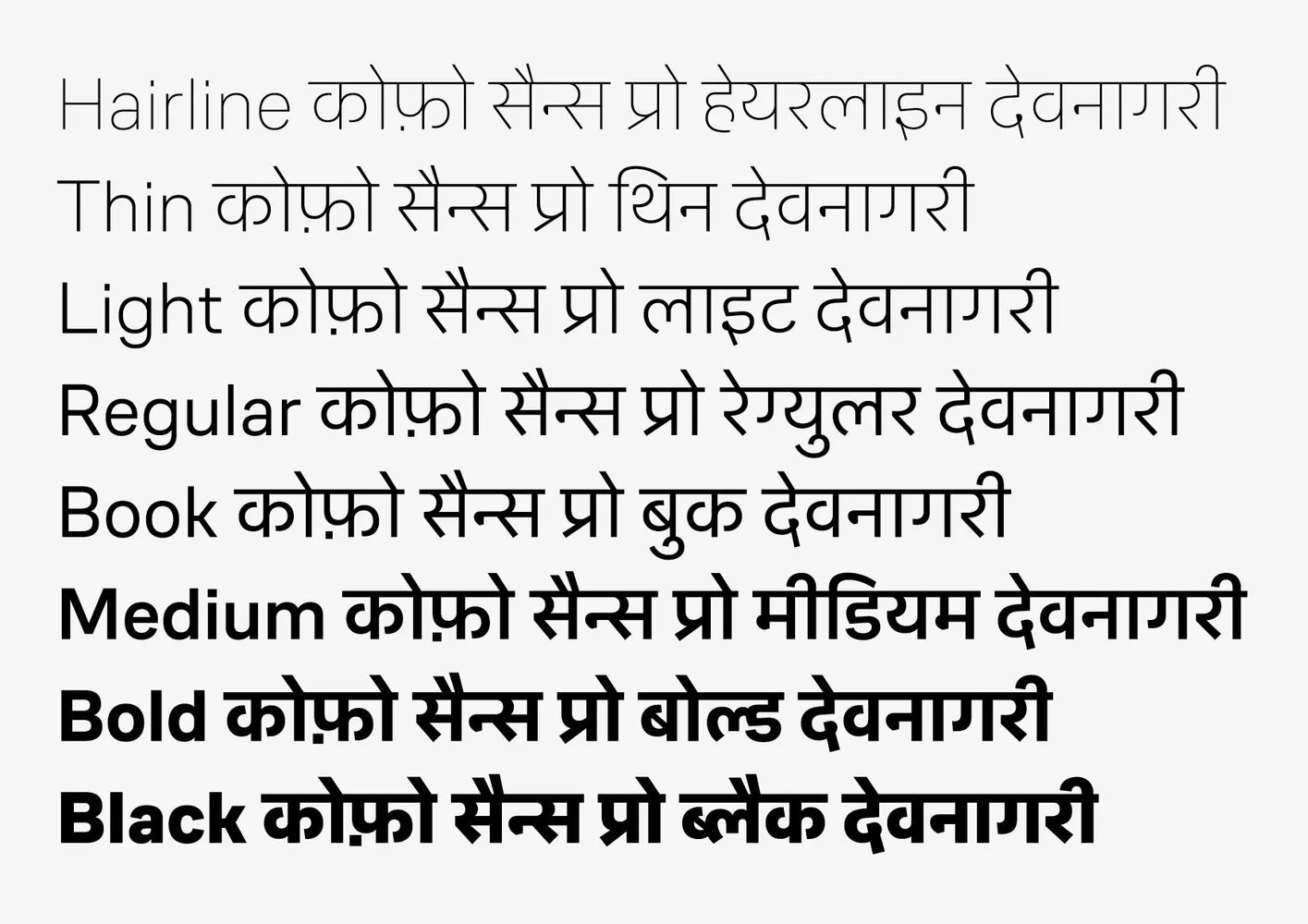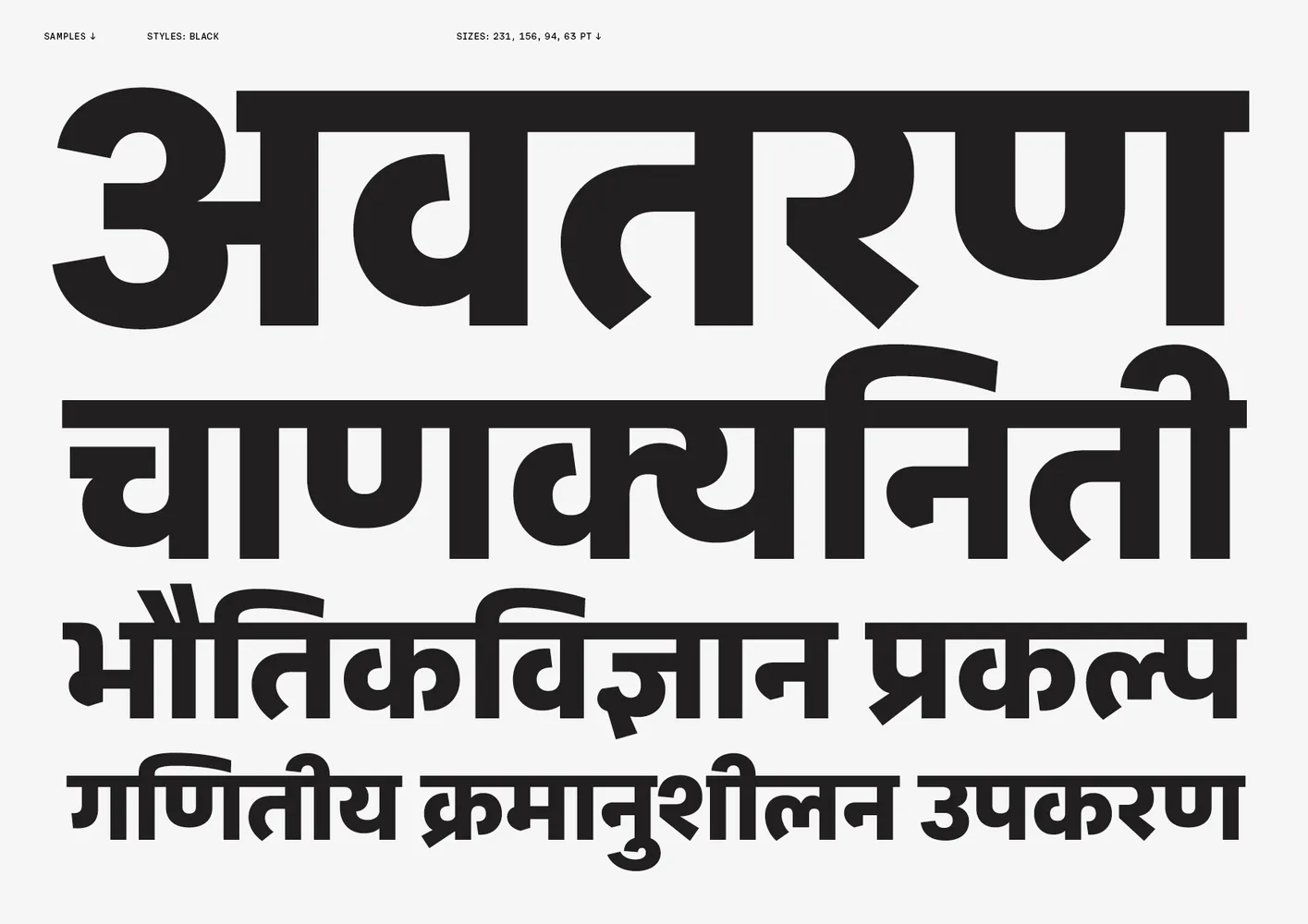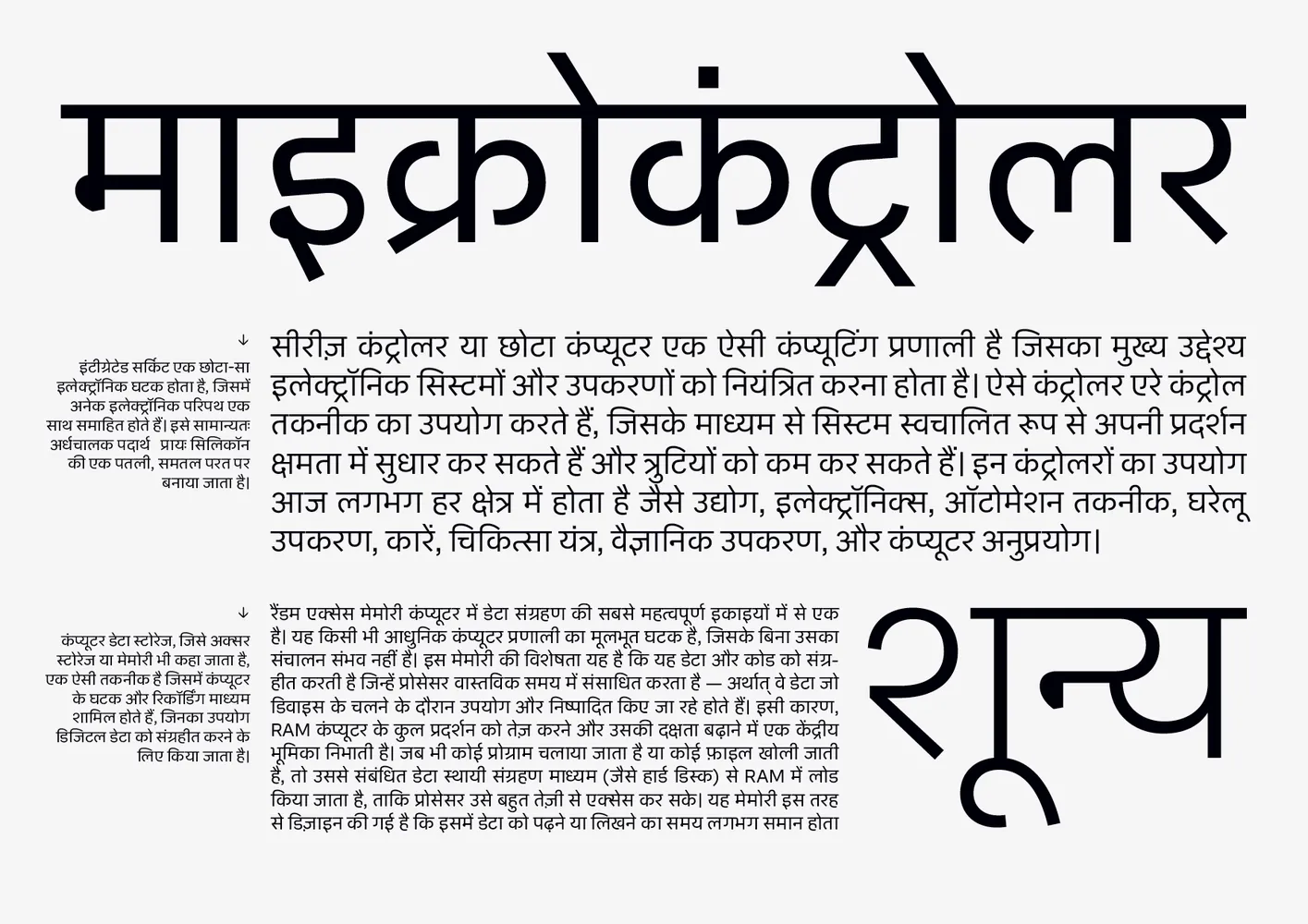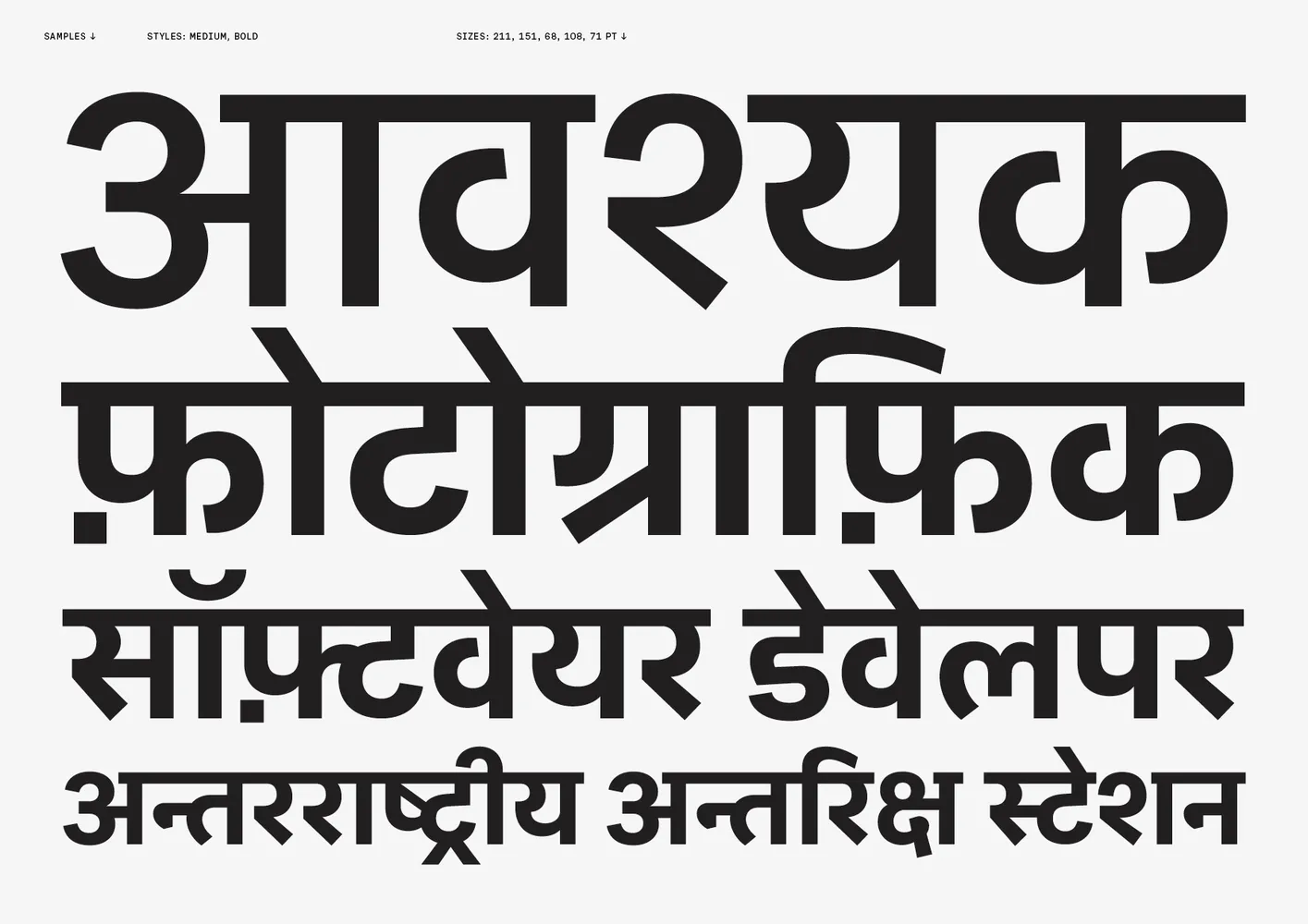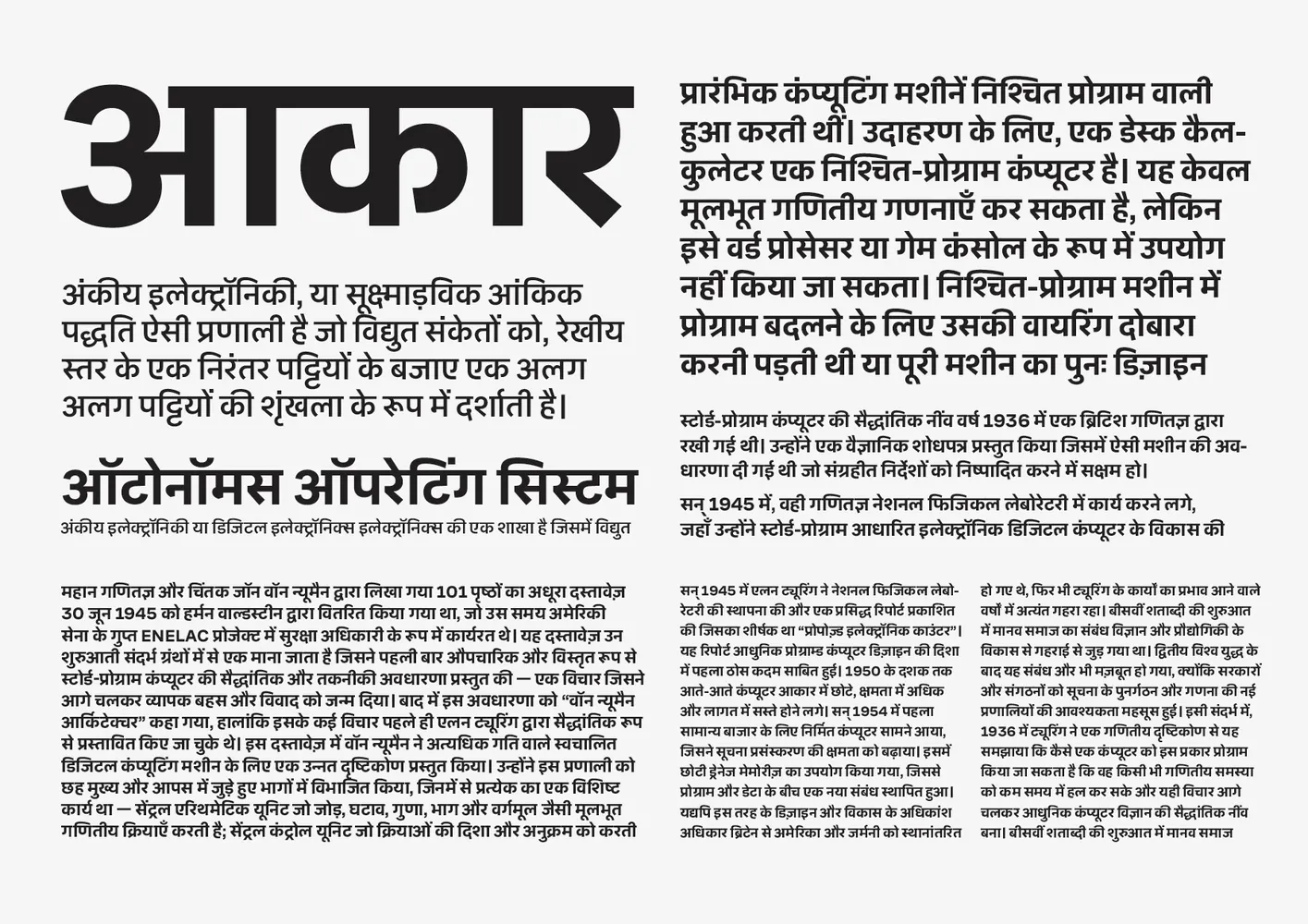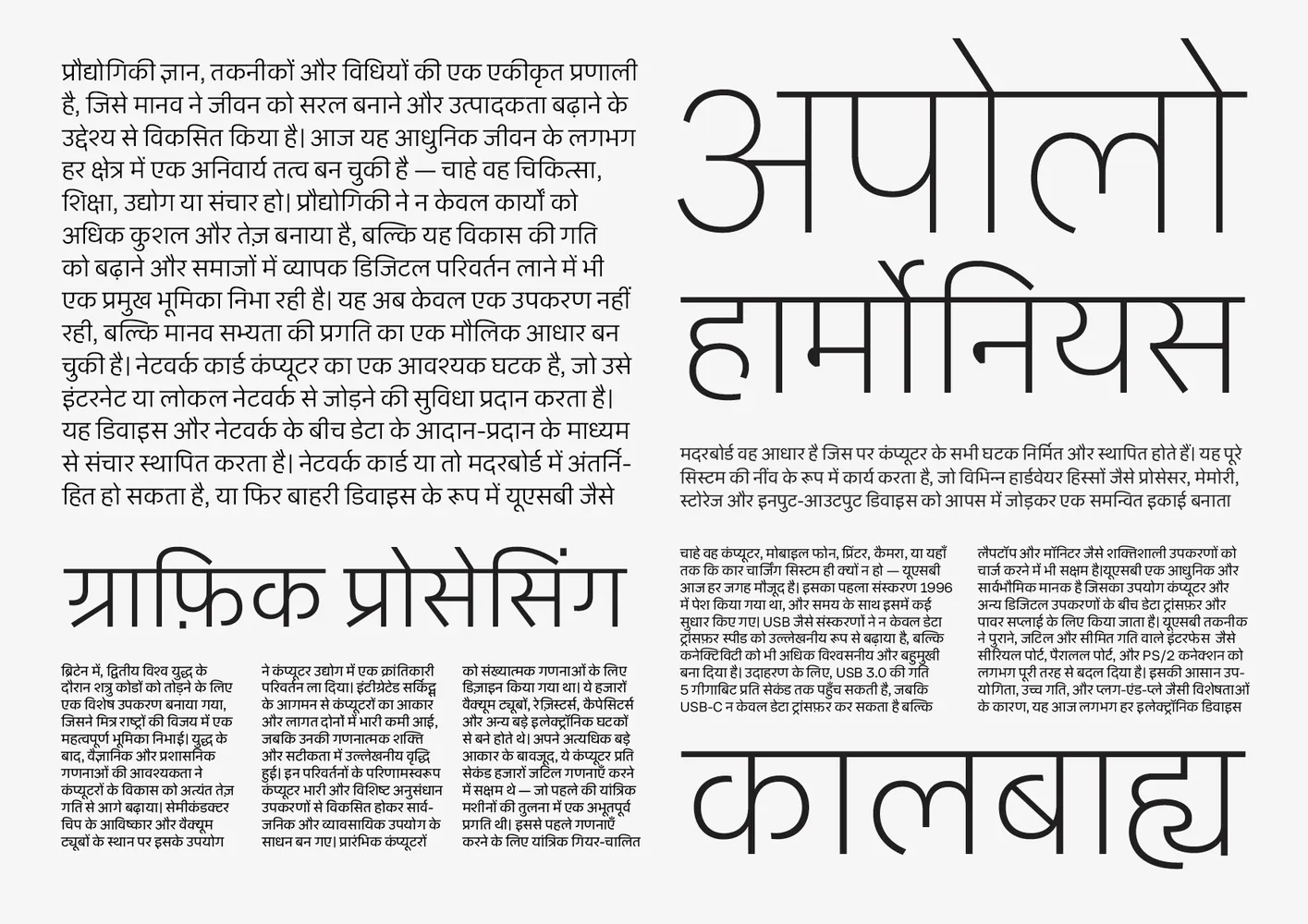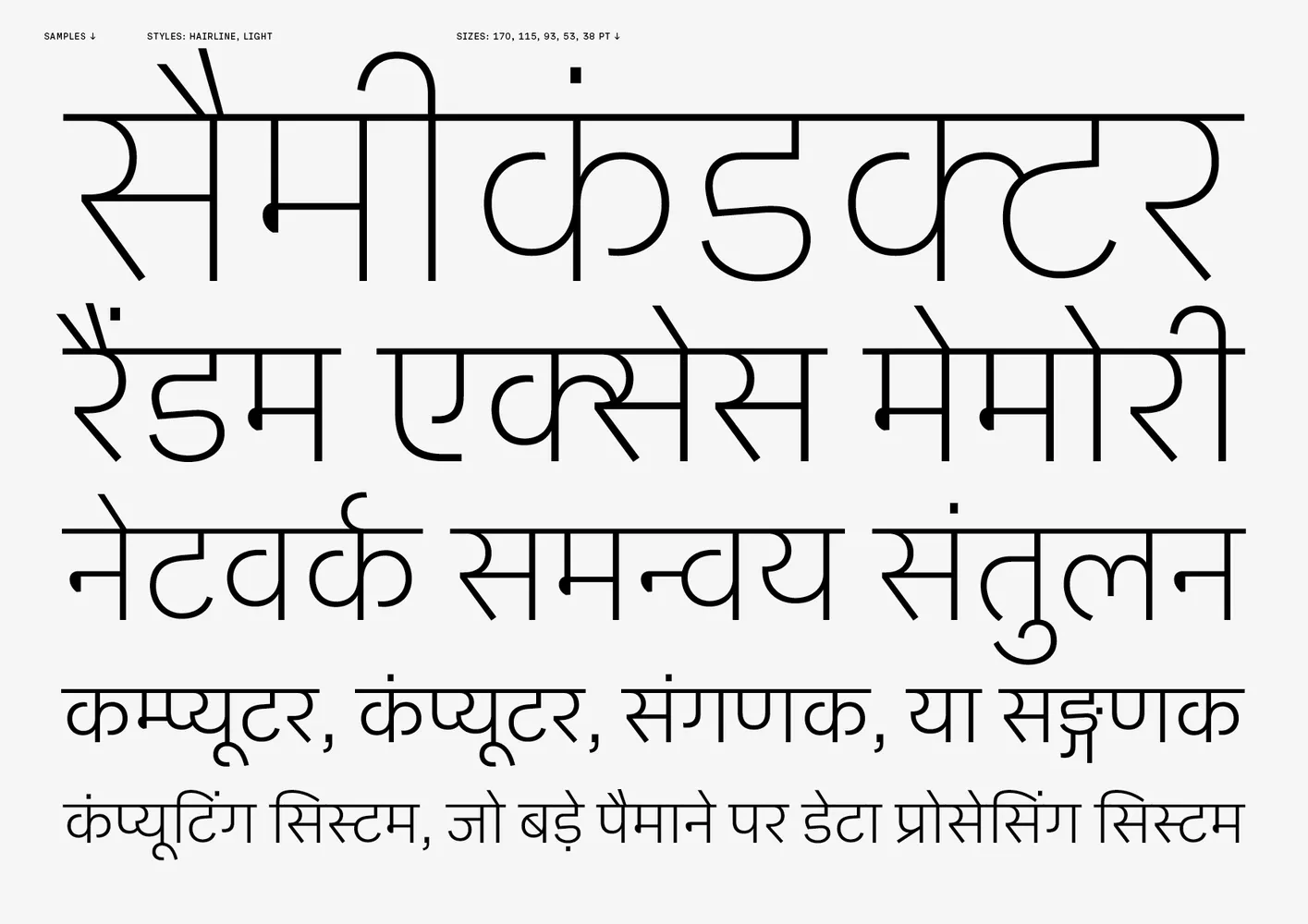
सैन्स देवनागरी
Лаконичный и простой, CoFo Sans совсем не похож на другие нейтральные гротески. Он строится на идее баланса между рациональностью и выразительностью, между строгой формой и живой интонацией. Сквадраченность форм, минимальный контраст, функциональность—всё это секрет уникальности шрифта.
Новая версия CoFo Sans Pro включает восемь начертаний по насыщенности, расширенную латиницу, кириллицу, вьетнамский язык и теперь деванагари. Деванагари сохраняет общий стиль семейства и при этом соблюдает традиции.
CoFo Sans Pro спроектирован для экранов. Он подходит для интерфейсов, брендинга и текста. Его рисунок изначально разрабатывался с идеей поддержки латиницы и кириллицы, а вскоре мы добавим поддержку иврита, а также грузинской и армянской письменностей. Получился универсальный шрифт с характером и авторской интонацией.